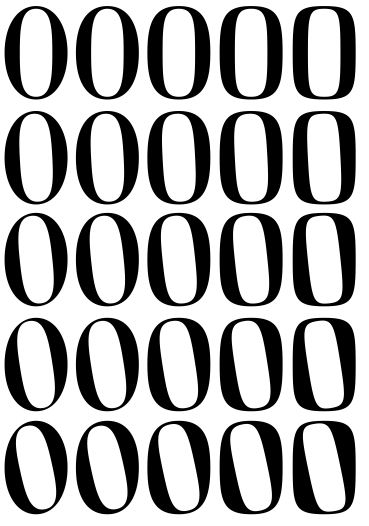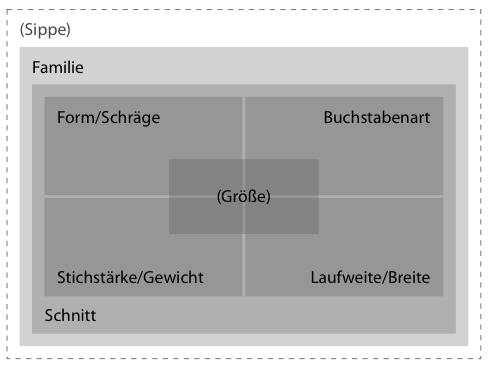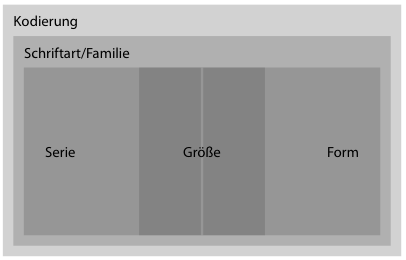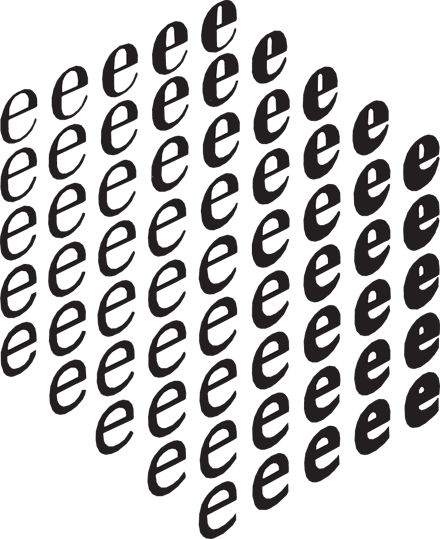
Begrifflichkeit/Zuordnung: Sippe, Familie, Schnitt, Gewicht usw.
ich bereite gerade einen LaTeX-Kurs vor, in dem ich auch auf Typografie eingehen möchte. Nun bin ich an die Stelle gelangt, an der es um Schriften und TeX’s Umgang mit diesen geht. Ich würde dass gerne von grob nach fein gliedern bin mir aber mit den Begrifflichkeiten uneins. Ich schreibe mal, was ich überlegt habe und bitte um Hinweise, Ideen und natürlich ggf. auch Korrekturen.
Die gröbste Kategorie ist für mich die Sippe, in der verschiedene Familien, i. d. R. eine Serifenschrift und eine Endstrichlose, zusammengefasst werden. Beispiel: Latin Modern
Die nächst feinere Stufe ist die Familie, die die verschiedenen Schnitte und Gewichte zusammenfasst. Als gängige Familien würde ich Serifenschrift*, Endstrichlose und Nichtproportinalschrift ansetzten. Beispiel: Latin Modern Roman oder Latin Modern Sans
So und nun gibt’s noch den Schnitt und das Gewicht, aber es scheint mir schwer, das scharf zu trennen. Aus dem Bauch würde ich jetzt als nächste Ebene den Schnitt ansetzten und zwischen aufrecht, kursiv und geneigt unterscheiden. Beispiel: Latin Modern Roman Italic
Als feinste Stufe folgt nun noch das Gewicht, bestehend aus leicht, fett, normal* usw. Beispiel: Latin Modern Roman Bold Italic
Aber wo in diesen Kategorien bringe ich nun die Kapitälchen unter. Sind sie ein eigener Schnitt und wenn ja sind dann kursive Kapitälchen auch ein eigener Schnitt?
Eng verwandt mit der Familie aber nicht synonym ist die Schriftart, die kann man ja kaum sinnvoll in diese Hierarchie integrieren oder? Wenn dann bestenfalls als Ebene unter die Familie oder eher über die Sippe …?
ich finde es auch schwierig, schnitt und gewicht in eine hierarchie zu bringen. immerhin haben alle fetten schnitte einer schrift ebenso etwas gemeinsam wie alle aufrechten und kursiven über die gewichte hinweg. ich würde aber dazu neigen, erst das gewicht und dann den schnitt anzusetzen – wie ja auch bei der üblichen benennungskonvention:
compatil [sippe] letter [familie] bold [gewicht] italic [schnitt].
der umgang mit schriftweiten bei der benennung schwankt. manche sehen das als weiteres attribut zwischen gewicht und schnitt (myriad bold condensed italic); andere betrachten die schmalen oder breiten schnitte jeweils als eigene familie (thesans condensed bold italic).
kapitälchen, unicase, schwungformen und ähnliches sehe ich als glyphenvarianten unterhalb der schnittebene – auch wenn sie aus technischen gründen bisweilen einen eigenen font darstellen.
der begriff ›schriftart‹ erscheint mir, wie dir, als eng bedeutungsverwandt mit ›schriftfamilie‹. letzteres betont etwas mehr die einzelnen familienmitglieder, ersteres eher die zusammengehörigkeit aufgrund eines gemeinsamen formprinzips.
Was die Engländer als Weight bezeichnen, heißt im Deutschen herkömmlicherweise Fette, nicht Gewicht. Als (optisches) Gewicht bezeichnet man allgemein, wie stark Elemente auf einer Seite hervortreten.
Als Schnitt bezeichnet man jede Ausprägung einer Familie. Es gibt also Schnitte mit verschiedenen Fetten, verschiedenen Breiten usw.
Der Ausdruck Schriftart ist zweideutig: Einerseits bezeichnet man damit eine bestimmte Familie (z. B. die Latin Modern Sans), andererseits eine geschichtliche/formale Gruppe (z. B. die Antiqua).
Die Kursive ist ja eine eigene Schriftart; erst nachträglich hat man Kursiven und Antiquae in gemeinsamen Familien zusammengefaßt. Heute faßt man noch mehr Schriftarten in Form von Sippen zusammen. Noch scheinen uns dabei Antiqua und Kursive einer Sippe enger zusammen zu gehören als beispielsweise Antiqua und Grotesk einer Sippe; vielleicht ist das in Zukunft aber anders. Man kann also auch die Kursive als gleichberechtigte Familie innerhalb einer Sippe betrachten.
Ich schlage folgende Hackordnung vor:
Sippe — Familie — Fette, Breite, Schräge (Fette, Breite und Schräge sind gleichberechtigte Eigenschaften)
z. B.: Latin Modern — Sans — Bold, Extended, Oblique
oder: Latin Modern — Roman Italic — Light, Narrow, Upright
Will man die Kursive nicht als eigene Familie anerkennen, muß man sie als eigene Eigenschaft führen:
Sippe — Familie — Starrschrift/Kursive, Fette, Breite, Schräge
z. B.: Latin Modern — Sans — Regular, Bold, Extended, Oblique
oder: Latin Modern — Roman — Italic, Light, Narrow, Upright
Das sind natürlich alles theoretische Überlegungen. Für einen LaTeX-Kurs ist darüberhinaus aber wichtig, wie LaTeX Schriften einteilt. Ein Schriftschnitt hat in LaTeX fünf Eigenschaften:
Encoding: Die Codierung, z. B. T1
Family: Der Familienname, z. B. Computer Modern Roman
Series: Fette und Breite, z. B. bold extended
Shape: Starrschrift/Kursive/Schrägschrift (Upright/Italic/Oblique)
Size: Die Größe, für die der Schnitt gestaltet ist, z. B. 10pt
Optische Größen haben wir schon auf der Liste, aber die technischen Optimierungen stehen noch nicht drauf …
Aber, je mehr ich mich jetzt mit diesen Gedanken befasse, fallen mir immer mehr fein abstufbare Dinge in der Micro-Typografie ein, die man qusi als weitere Dimensionen unseer Sippe auffassen könnte. Leider fallen mir im Moment die Fachbegriffe nicht ein (leise rieselt offenbar schon mein Kalk), drum auch mal grafisch: